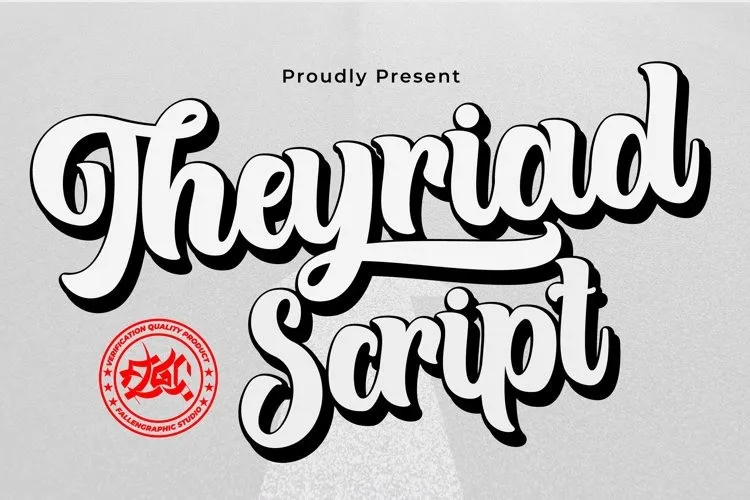
Elesriad Font é uma fonte script suave e pessoal com um toque retro perfeito para os designers que desejam dar um toque especial a seus projetos. Com seu charme único, este tipo de texto é ideal para uso em logotipos fotográficos, frases memoráveis, capas de álbuns e cartões de visitas. Além disso, elesriad Script se destaca como uma opção perfeita para adicionar um toque autêntico a trabalhos que vão desde os mais simples até os projetos mais sofisticados. Seja você um designer de logotipos ou criativo em busca de um estilo atraente e único, elesriad Script é o tipo certo para destacar seus design inovadores. Suas linhas fluidas e sua personalidade garantem que qualquer projeto no qual ele seja usado se destaque, tornando-o uma escolha inteligente para aquelas pessoas que buscam trazer um toque autêntico a seus trabalhos de arte digital.